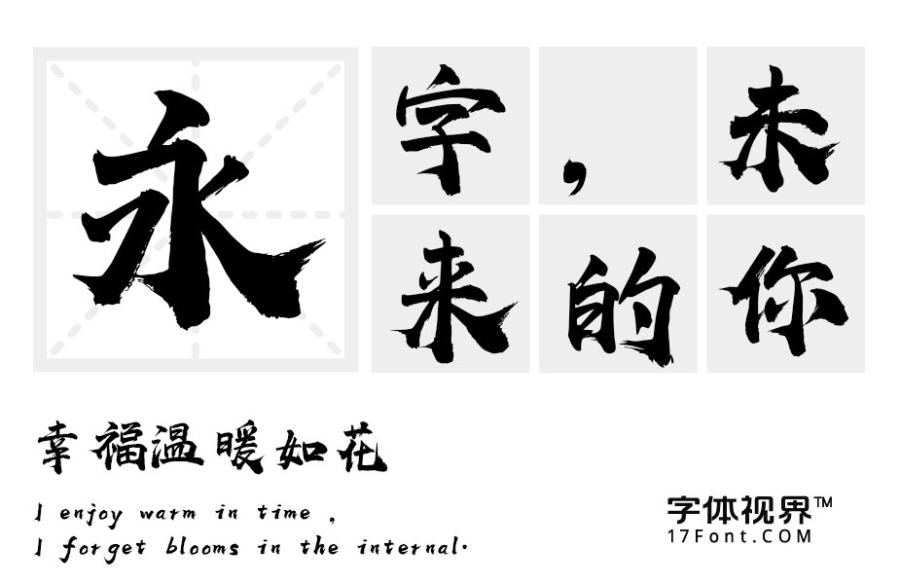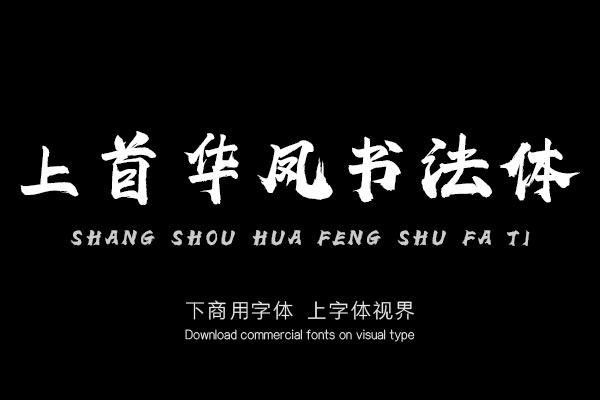
上首华凤书法体,字体风格稳重呈方块形,字体笔画竖折处细节处理,是此套字库的亮点。字库整体特征坚硬、有力,具有现代、国际化的指向性,适用于搭配标志、广告标语、商业......购买须知:“下载服务费”与“字体VIP”所获得字体 仅用于个人非商用, 商用请联系付费授权。本字体为电脑用字,手机没有root权限不支持直接手机换字(手机如何root,请自行百度搜索教程)。购买前请先 了解清楚后再付款 ,字体为虚拟产品无法回收 一旦购买不支持退款。